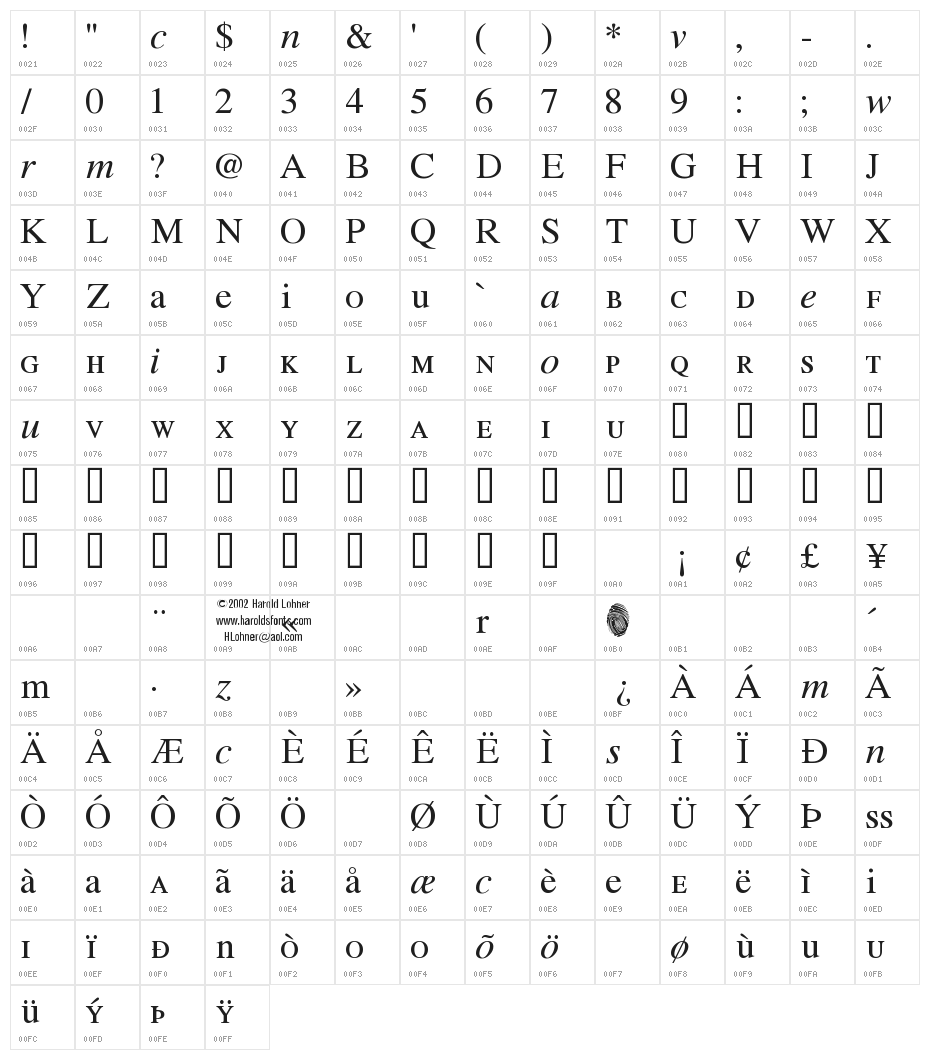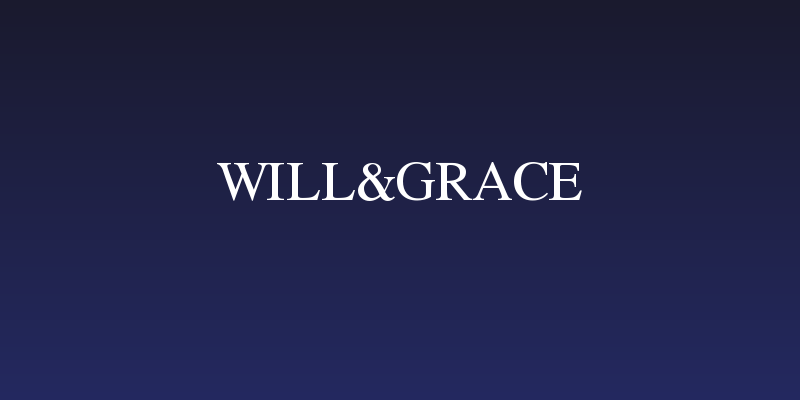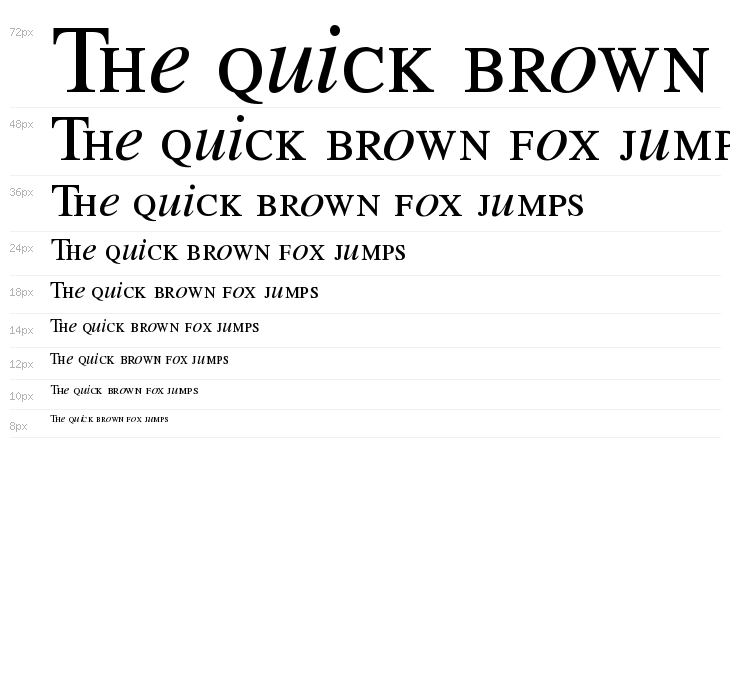
Will&Grace Font
✎ Serif
Fonts by Harold Lohner - www.haroldsfonts.com
| Kategorien | Serif |
| Gesamtstil | Classic |
| Anwendungsfall | Headlines, Body text, Logos |
| Vorgeschlagene Projekte | Ideal for use in editorial design, book covers, formal invitations, and branding materials that require a touch of elegance and sophistication. |